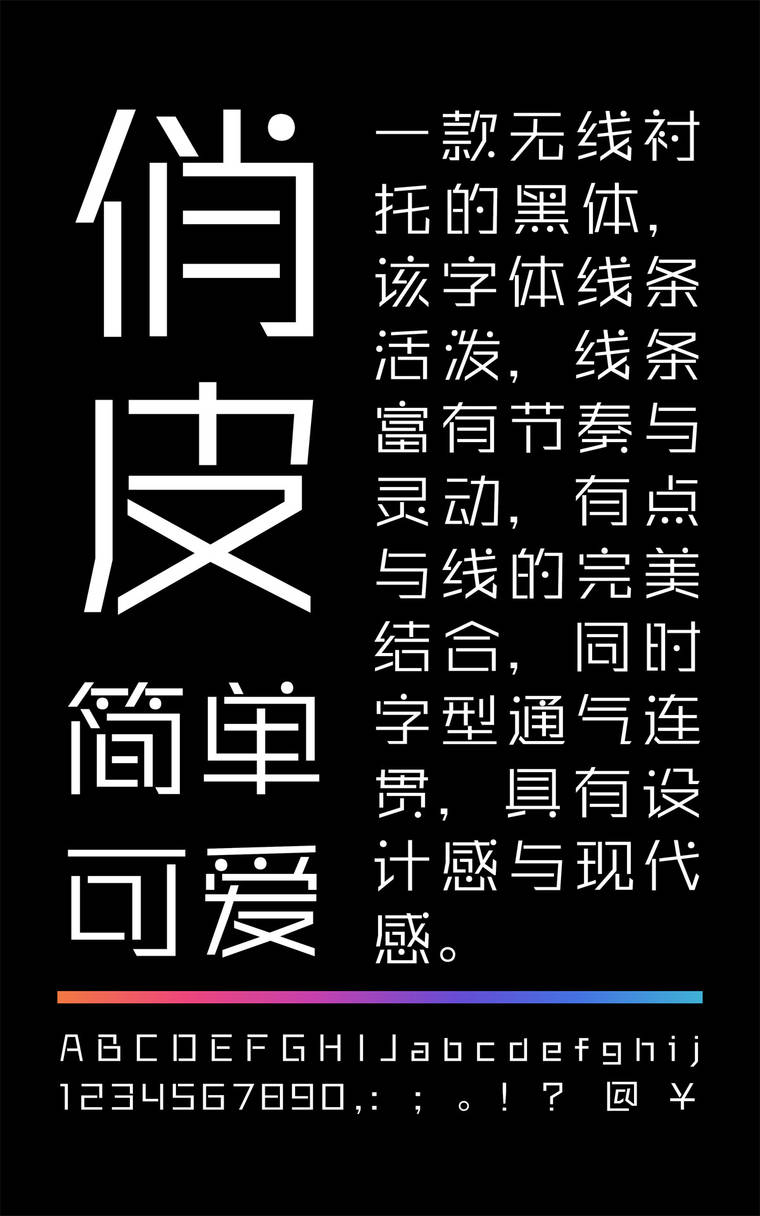
锐字锐线俏皮简1.0
锐字锐线俏皮简1.0,这款字体结构工整、笔画清晰,兼顾美观与易读性,适用于标题、正文、海报、包装、LOGO 等多种场景。字形优雅稳定,风格百搭耐看,适配日常排版与创意设计,让文字呈现更舒适、更具质感。锐字锐线俏皮简1.0一笔一画,皆是细节,以均衡的比例、流畅的线条打造舒适视觉体验,字形端正大气,风格简约现代。无论是商业设计、品牌宣传还是日常排版,都能轻松驾驭,让文字更有格调与力量。锐字锐线俏皮简1.0字体下载。
字体特征:锐字锐线俏皮简是一款无线衬托的黑体,该字体线条活泼,线条富有节奏与灵动,有点与线的完美结合,同时字型通气连贯,具有设计感与现代,感突出全新的笔画特征,能够适用于艺术设计、包装印刷、签名设计、图形设计等领域。